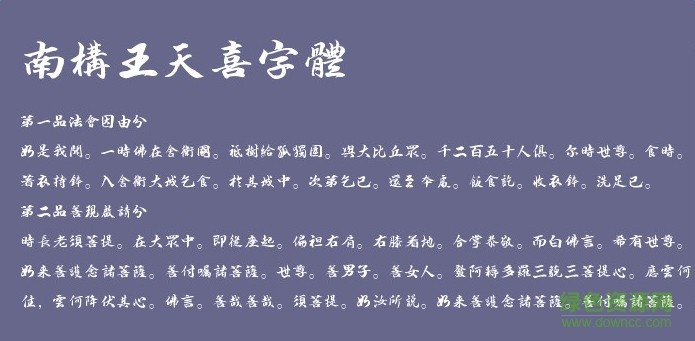
南構(gòu)王天喜字體是一款南構(gòu)類行書風(fēng)格字體軟件,由著名書法家王天喜傾心創(chuàng)作而成,字體飄逸卻又不失工整,整體效果得體大方,非常耐看,感興趣的朋友歡迎來綠色資源網(wǎng)下載體驗!
南構(gòu)王天喜字體由王天喜先生書寫字型的一款行書字體,王天喜,浙江省江山市峽口鎮(zhèn)人,自幼酷愛書法,在繁忙的事業(yè)中不忘筆耕,其書博古通今,顧盼生輝,這是一款具有儒雅中國風(fēng)的行書字體。